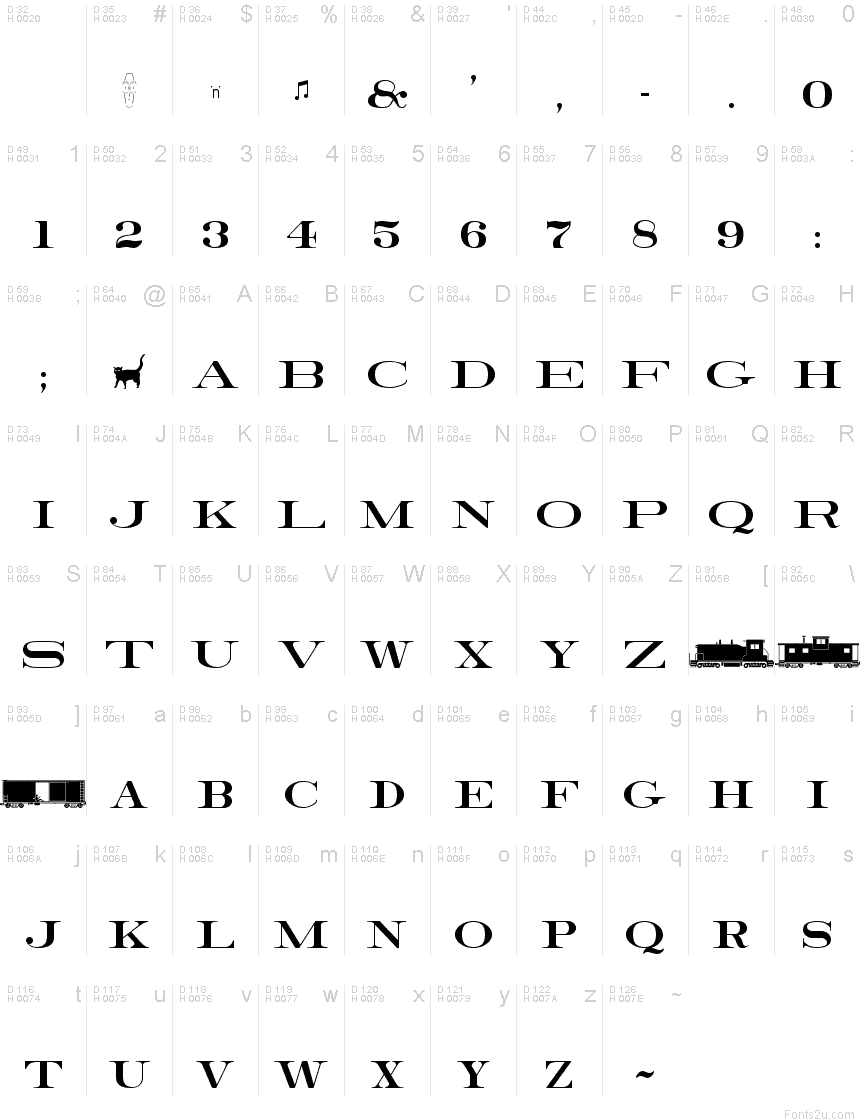
Railroad Roman, darmowy krój szeryfowy (wyłącznie wielkie litery) autorstwa Benna Coifmana z 1994 roku, nawiązuje do dawnego liternictwa kolejowego dzięki szerokim, masywnym formom i łagodnie wyciętym łukom. Litery wyglądają jak stworzone do szyldów dworcowych i rozkładów jazdy: są solidne, wyprostowane i lekko ozdobne, a zaokrąglone łączenia sprawiają, że ich ciężar nie staje się przytłaczający.
To sprawia, że jest to naturalny wybór darmowego fontu do tytułów w stylu western, brandingów retro, nagłówków plakatów, okładek książek czy kart menu, gdzie potrzeba odrobiny amerykańskiego klimatu z epoki kolei. Sprawdza się również w krótkich monogramach i inicjałach, ponieważ wielkie litery mają mnóstwo charakteru dzięki swoim masywnym blokom i wgłębionym detalom.